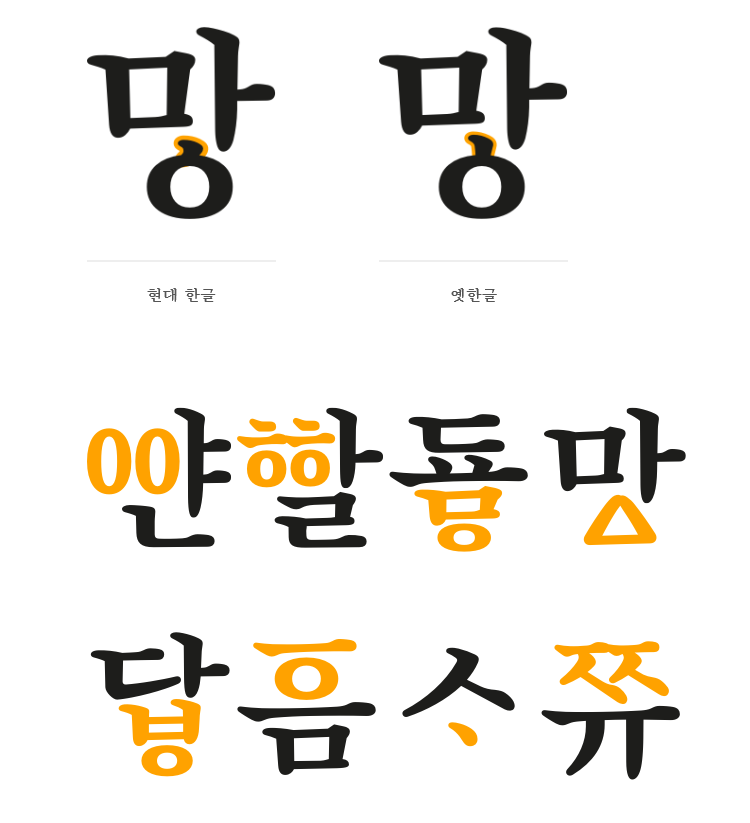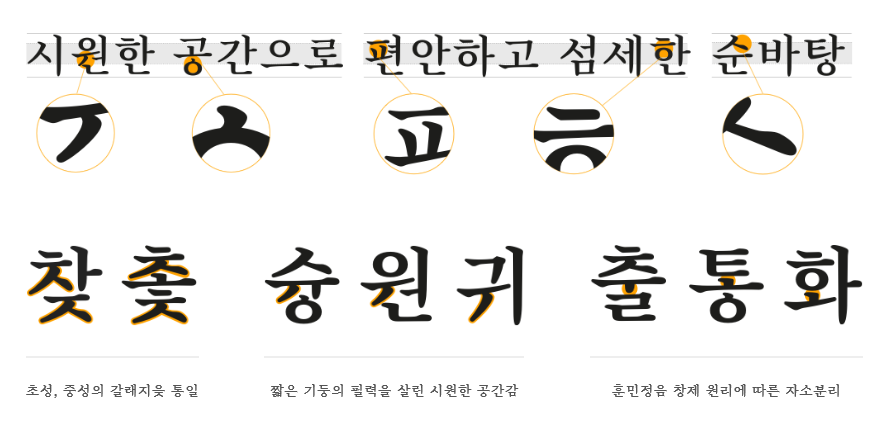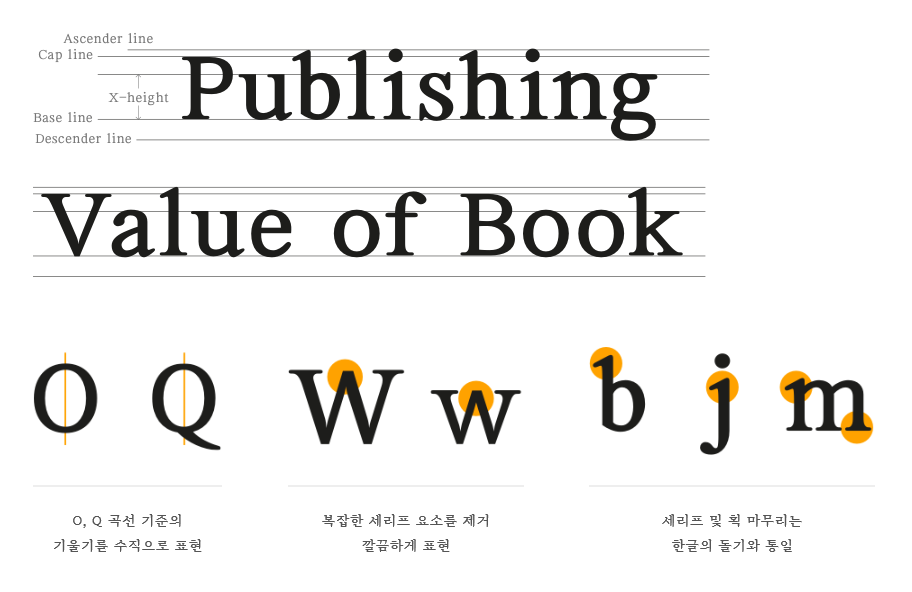
한국출판문화산업진흥원, 오픈소스형 디지털 폰트인 순바탕체 개발
한국문화출판문화산업진흥원에서 오픈소스형 디지털 폰트 순바탕체를 개발해 보급한다.
상업용 서체 사용에 따른 비용 부담 및 지적 재산권 분쟁 방지를 목적으로 개발된 순바탕체는 바탕체의 전통적인 요소들은 유지하되, 정확한 표현과 맺음으로 전통적인 아름다움을 살리고 현대화함으로써 디지털 환경에서 활용성을 높였다. 또한 영문, 한글과의 조화성, 본문용 서체로써 심미성과 활용성도 신경써서 제작했다.
순바탕이라는 이름은 ‘다른 것이 섞이지 아니하여 깨끗하고 맑은 바탕’이라는 의미다. 이름에 걸맞게 서체의 특징 또한 자음과 모음의 구분, 여백, 세리프의 형태가 뚜렷하게 구별되는 특징을 갖고 있다.
무엇보다 이번 순바탕체의 개발에서 특히 인상적인 부분은 옛한글 5,299자가 구현되었다는 것이다. 현대한글과도 조화롭게 어울리며, 자음과 모음, 자소의 형태, 시각적인 비율, 착시현상 등 환경 변화에 따른 미적 디자인의 원칙을 기반으로 제작이 되었다. 향후 출판시장에서도 순바탕체와 함께 사용 빈도가 계속해서 증가할 것으로 기대된다.
출판에서의 쓰임에 맞게 영문 폰트 한글의 돌기나 획의 마무리와 통일성을 느낄 수 있도록 제작되었으며, 영문의 펜글씨 영향으로 인한 굵기 차를 한글의 붓글씨 느낌으로 완만하도록 맞춰주었다. 실제 폰트 소개페이지에서 타이핑을 해보면 한글과 영문이 조화롭게 보여진다. 영문 말고도 KS 심벌 1,369자와 일본어 189자(히라가나 93자, 가타가나 96자)도 지원한다.